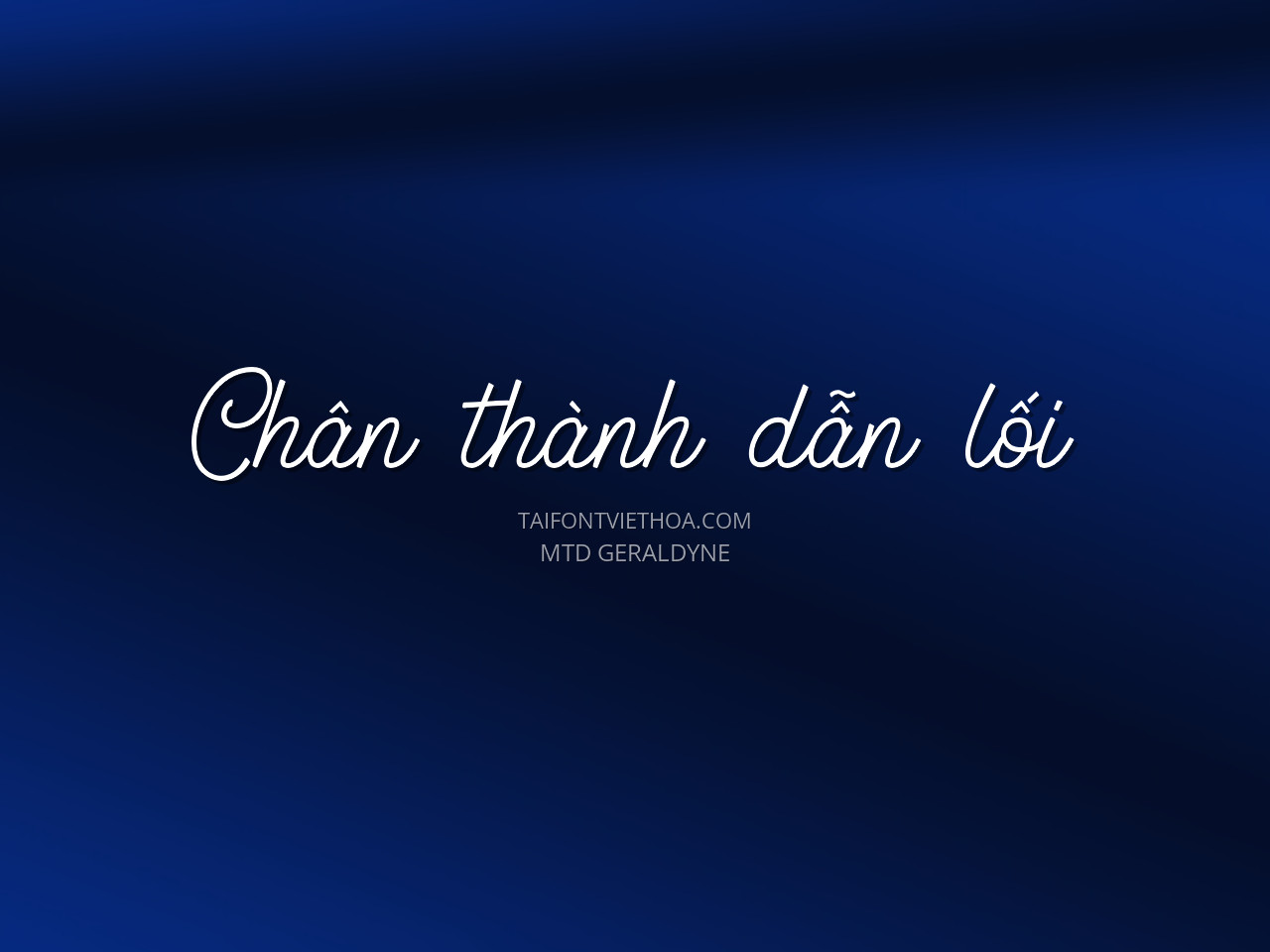
Font việt hóa MTD Geraldyne
Giới thiệu về font Geraldyne
Geraldyne là một font script mang phong cách chữ ký (signature style), được thiết kế bởi Motokiwo Type (MTD). Font gây ấn tượng với các đường nét uyển chuyển, tinh tế, mô phỏng nét bút tay thật một cách tự nhiên và mềm mại. Với vẻ ngoài trang nhã, thanh lịch nhưng vẫn đậm chất cá nhân, Geraldyne là lựa chọn lý tưởng cho những dự án cần thể hiện sự cao cấp, nhẹ nhàng và mang dấu ấn riêng. Phiên bản Việt hóa được thực hiện bởi chính MTD, hỗ trợ đầy đủ tiếng Việt và hơn 70 ngôn ngữ quốc tế, tạo điều kiện tối ưu cho các thiết kế toàn cầu.
Đặc điểm thiết kế và ứng dụng của font Geraldyne
Font sở hữu cấu trúc chữ mảnh mai, thanh thoát với các liên kết linh hoạt giữa các ký tự. Nét chữ có độ nghiêng nhẹ, tạo cảm giác tự nhiên như đang viết tay thực thụ. Font cũng tích hợp nhiều ligatures và ký tự thay thế (alternates) để người dùng dễ dàng biến tấu theo phong cách riêng. Geraldyne phù hợp nhất trong các thiết kế đề cao tính cảm xúc, thẩm mỹ và sang trọng.
Ứng dụng lý tưởng: thiết kế logo cá nhân, bìa sách, bao bì mỹ phẩm, thiệp mời, tiêu đề blog, poster nghệ thuật và các sản phẩm truyền cảm hứng. Ngành nghề phù hợp: wedding planner, mỹ phẩm cao cấp, thời trang nữ, studio ảnh, lifestyle brand, thương hiệu cá nhân và các dự án sáng tạo đòi hỏi yếu tố thẩm mỹ cao.